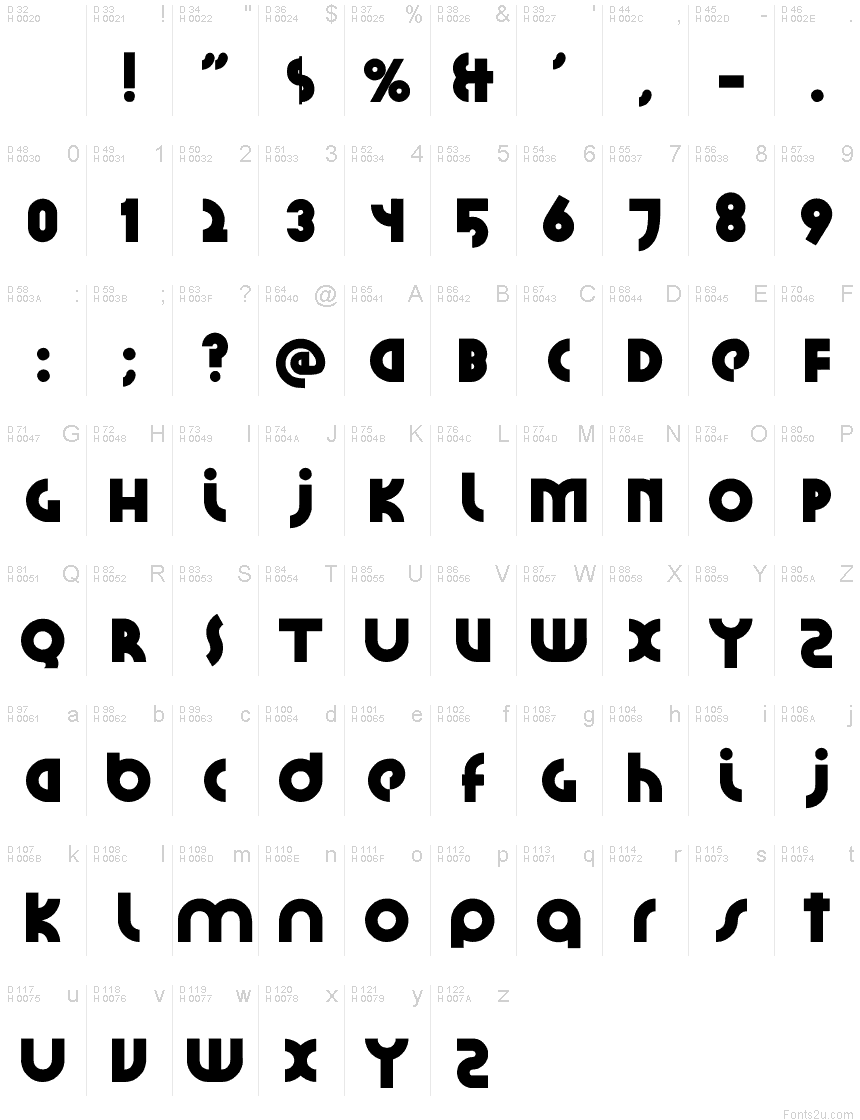
Santiako Bold to darmowy krój pisma typu display w stylu retro, o masywnym, zaokrąglonym rytmie i wyrazistym klimacie lat 70. Litery łączą szerokie łuki z surowymi, pionowymi cięciami, dzięki czemu kształty sprawiają wrażenie miękkich i ciężkich zarazem, a zabawny, dynamiczny charakter sprawia, że geometria nie staje się chłodna.
Ten darmowy font świetnie sprawdzi się na plakatach, okładkach płyt, w brandingu kawiarni, na ulotkach festiwalowych czy planszach tytułowych, wszędzie tam, gdzie krótki tekst potrzebuje ciepłego, vintage’owego akcentu. Sprawdza się też w logo i wyróżnionych cytatach, ponieważ grube, niemal modularne krzywe sprawiają, że nawet proste słowa stają się graficzne i zapadają w pamięć.